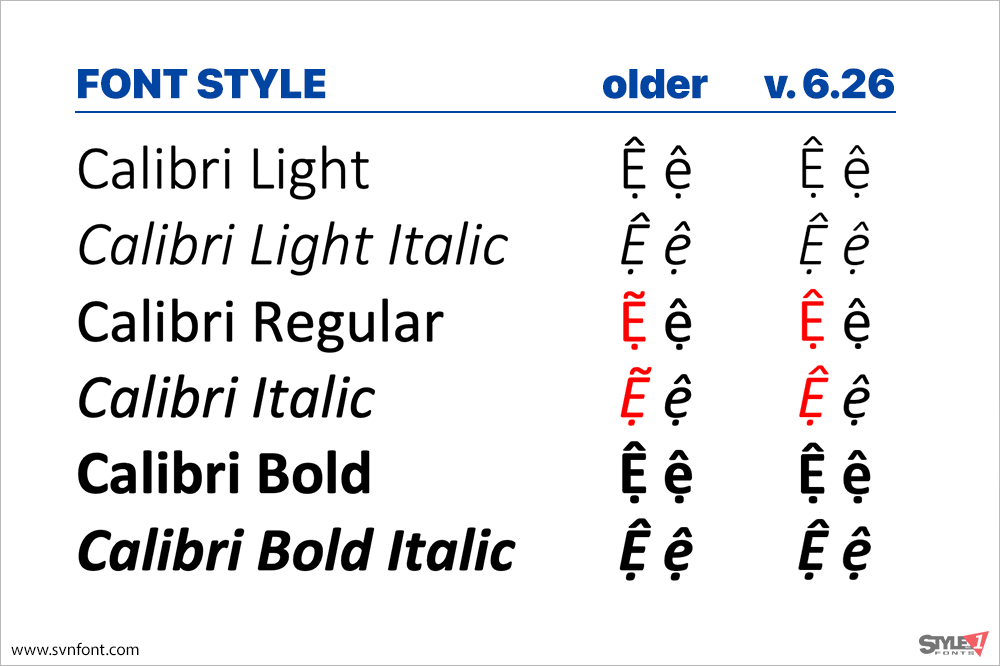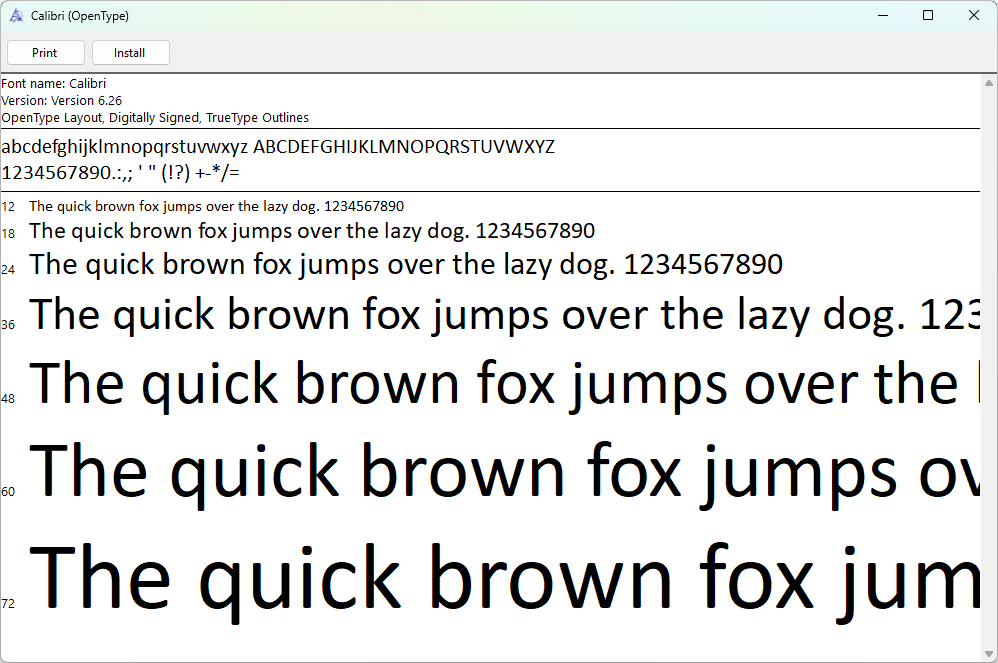
Chắc hẳn ai sử dụng Microsoft Office đều biết đến Calibri, typeface mặc định trên bộ phần mềm văn phòng nổi tiếng của Microsoft. Nhưng có 1 lỗi ở typeface này là ký tự “Ệ” (một số bản cũ hơn có thêm lỗi trên ký tự “Ộ”) trên 2 styles: Calibri Regular và Calibri Italic bị hiển thị sai dấu mà bạn chắc nhiều lần gặp phải khi gõ đến các ký tự này. Điều này gây ra nhiều sự bất tiện trong sử dụng hằng ngày, đặc biệt là trong các nội dung trang trọng. Đến nỗi bây giờ, người ta tránh dùng Calibri mỗi khi gõ văn bản.
Calibri là một họ font sans-serif kỹ thuật số được thiết kế theo phong cách nhân văn hoặc hiện đại. Calibri được thiết kế bởi Luc(as) de Groot trong khoảng thời gian 2002 – 2004 và được phát hành lần đầu vào năm 2007 kèm theo Microsoft Office 2007 và trên Windows Vista cùng năm. Nó trở thành font mặc định trên Word thay thế cho Times New Roman; trên PowerPoint, Excel… thay thế cho Arial. De Groot đã mô tả thiết kế bo tròn tinh tế của nó là có sự “ấm áp và mềm mại”.
Lỗi ngớ ngẩn này được Microsoft “giữ lại” trong suốt 15 năm như một “đặc trưng” của Calibri, mặc dù đã có rất nhiều lời phàn nàn từ người dùng Việt trên các diễn đàn cũng như Feedback Hub, tuy nhiên tất cả cũng chỉ là sự ngó lơ từ ông lớn. Thậm chí, phiên bản thương mại của font vẫn còn lỗi này trên một số trang như Myfonts, Fontshop… Mãi đến bản cập nhật 22H2 gần đây (09/2022) của Windows 11, Calibri mới chính thức được sửa lỗi.